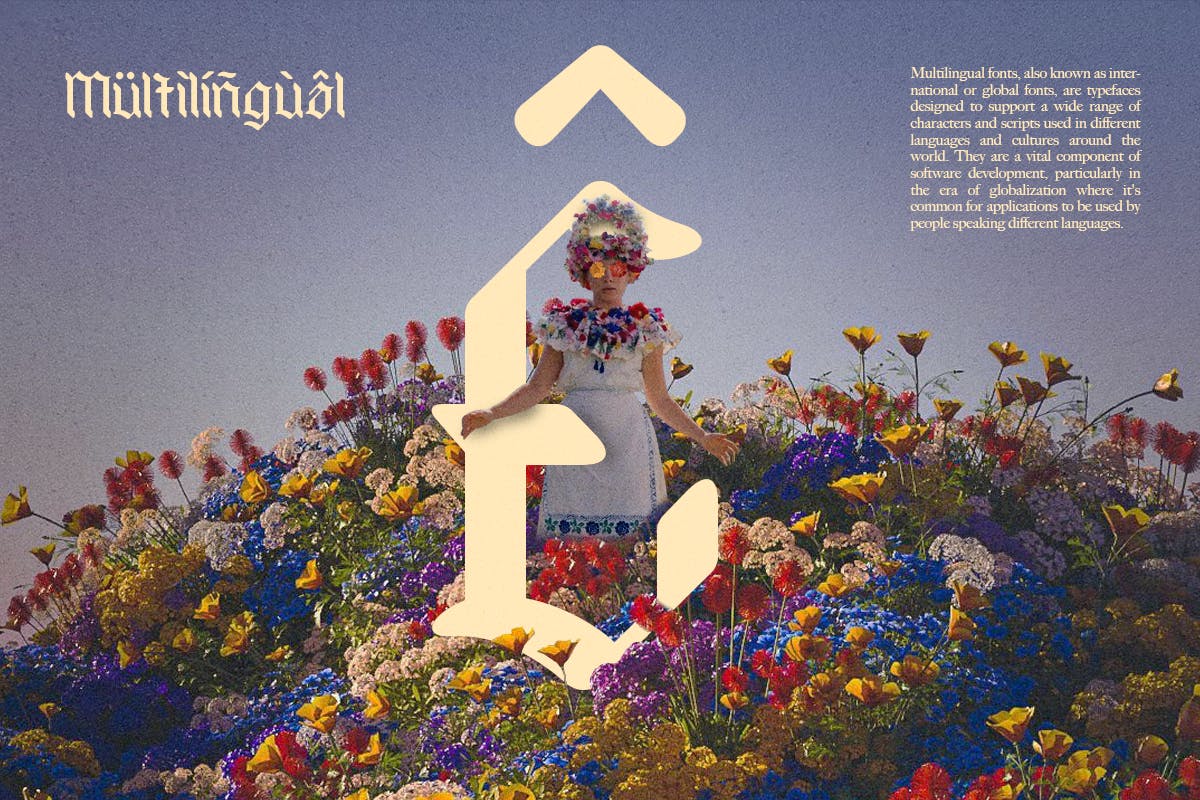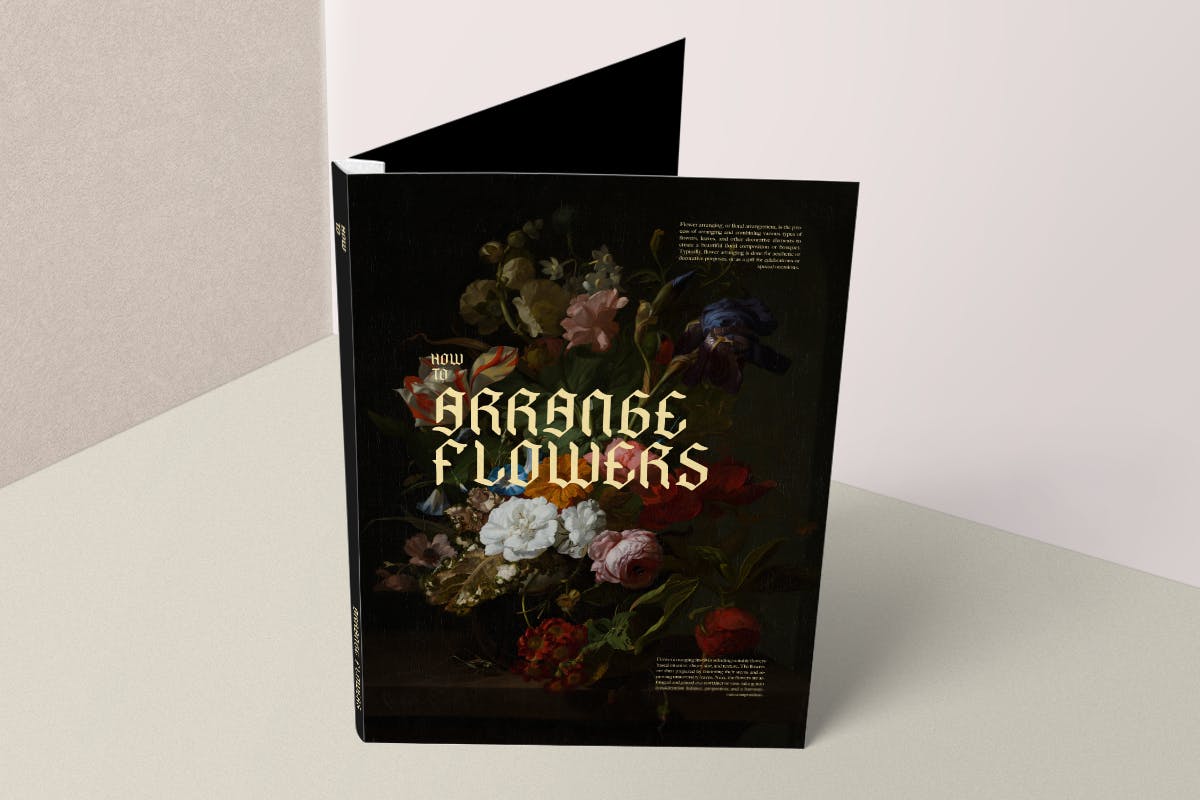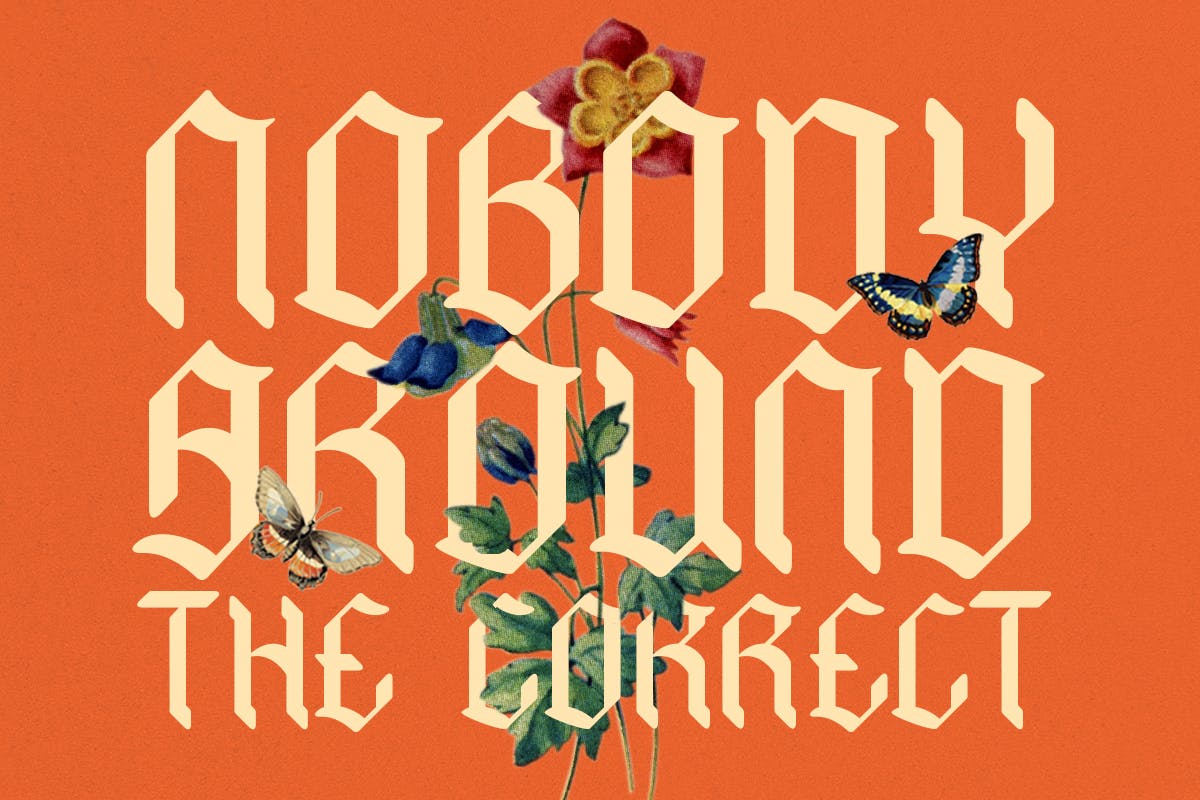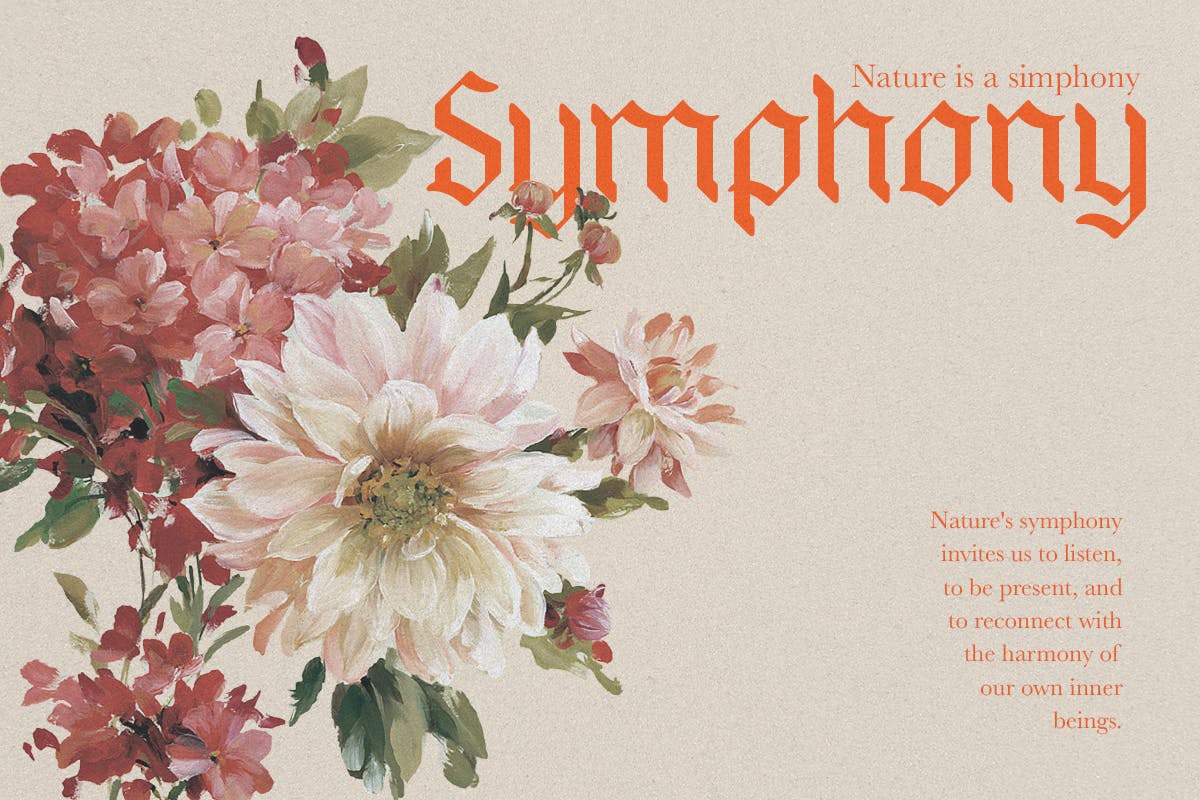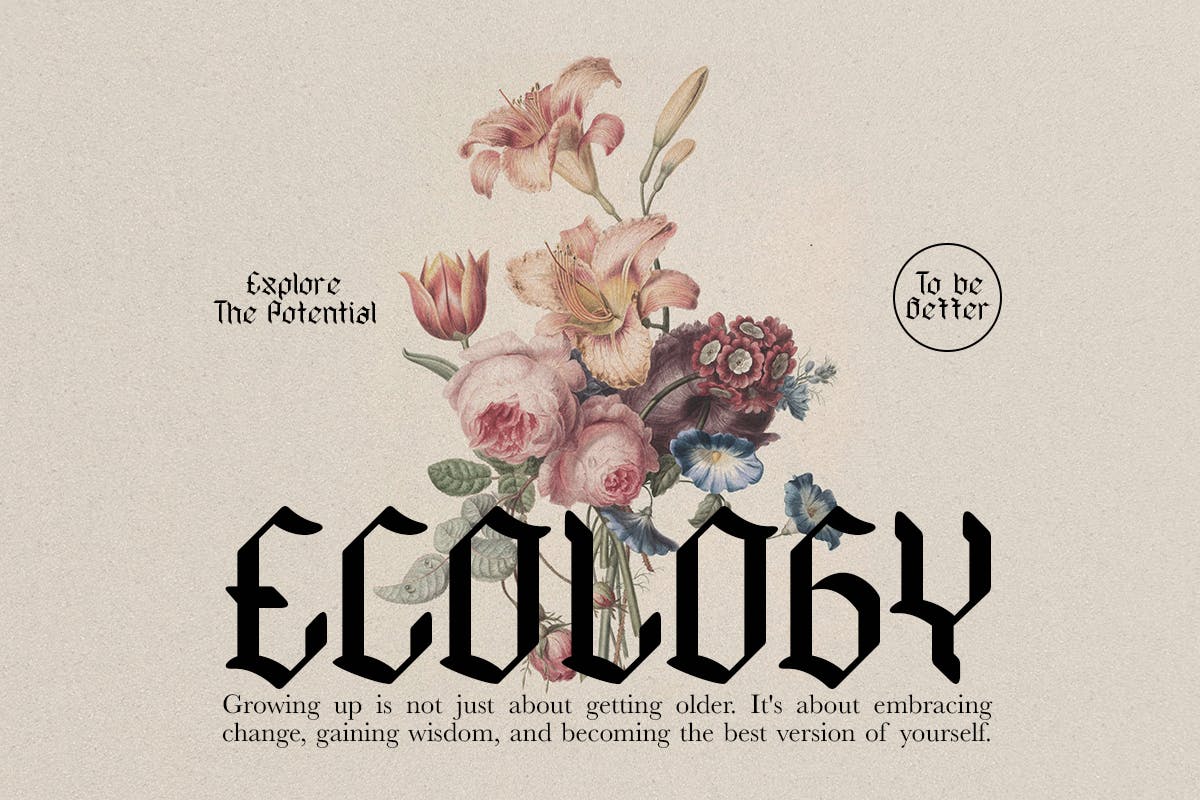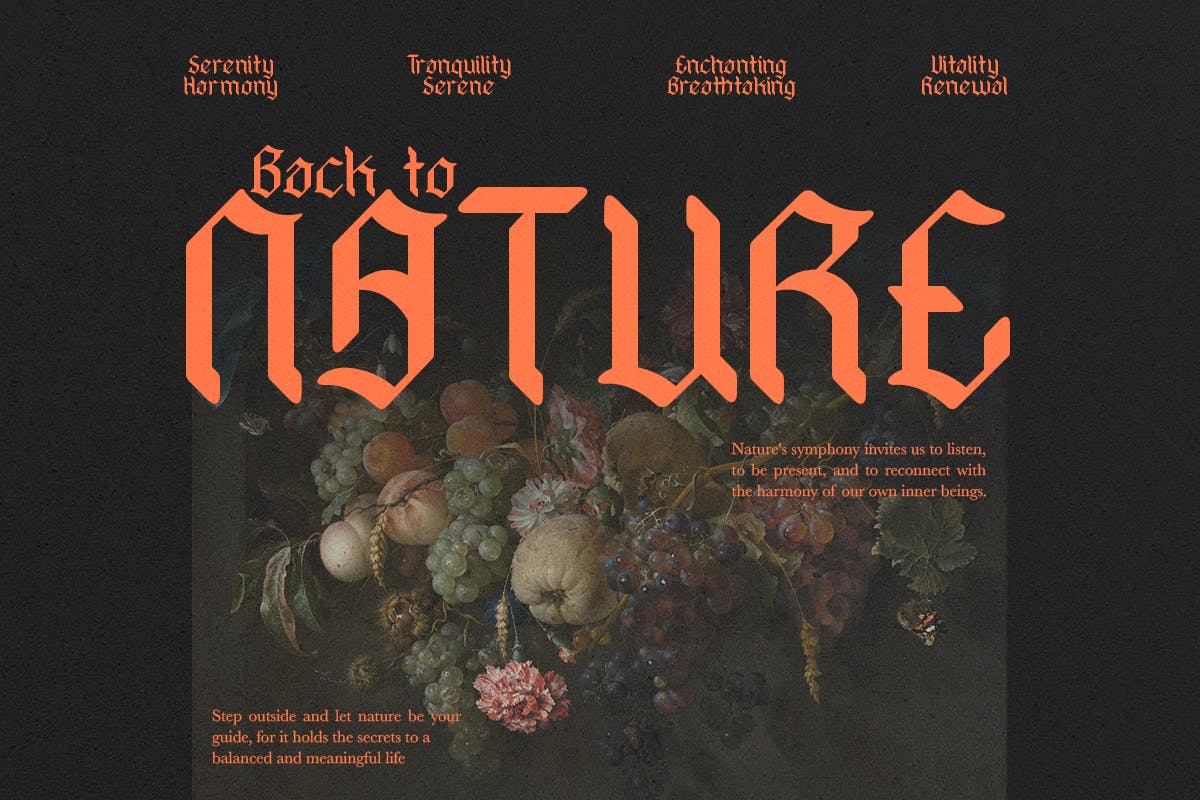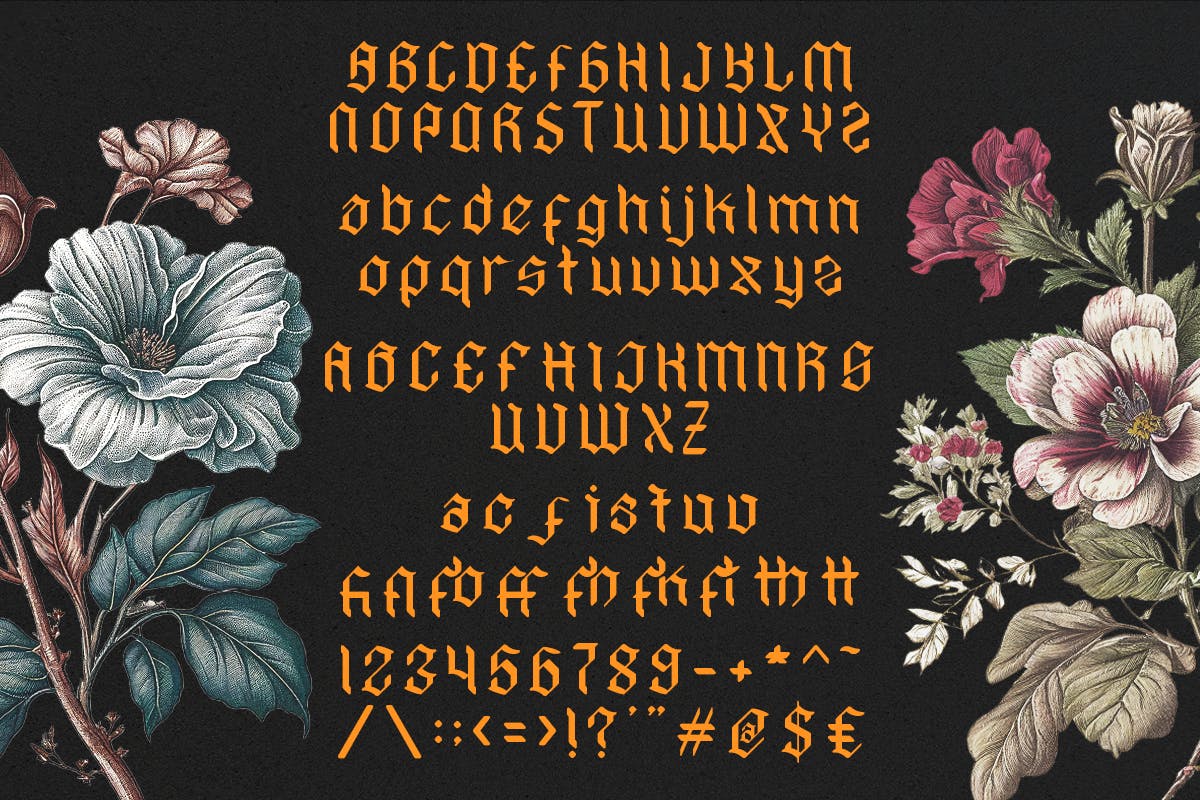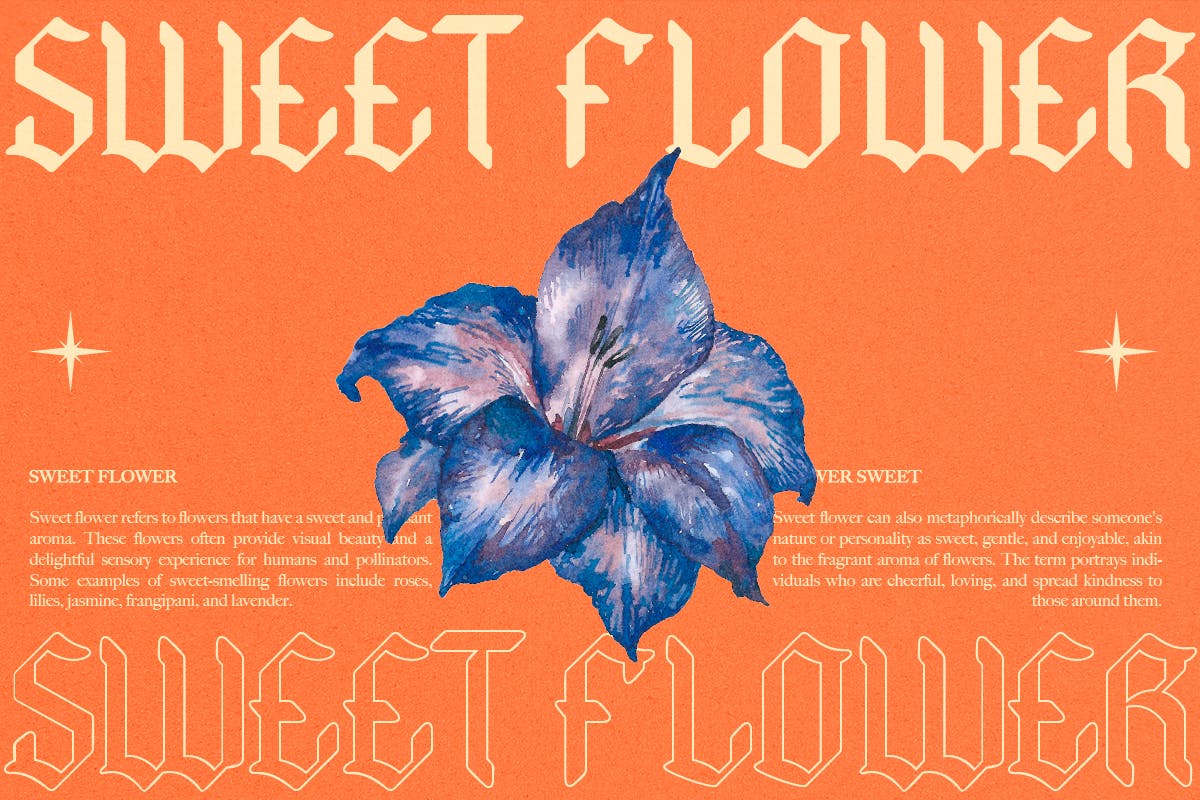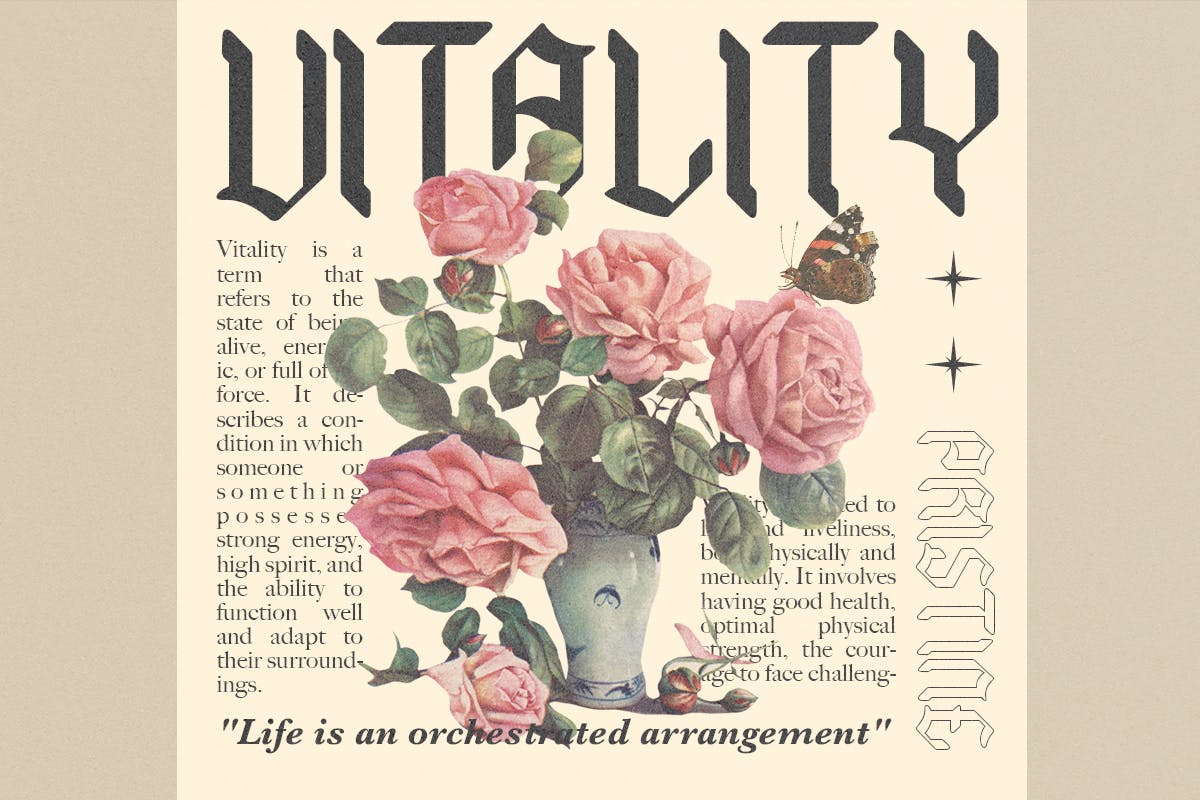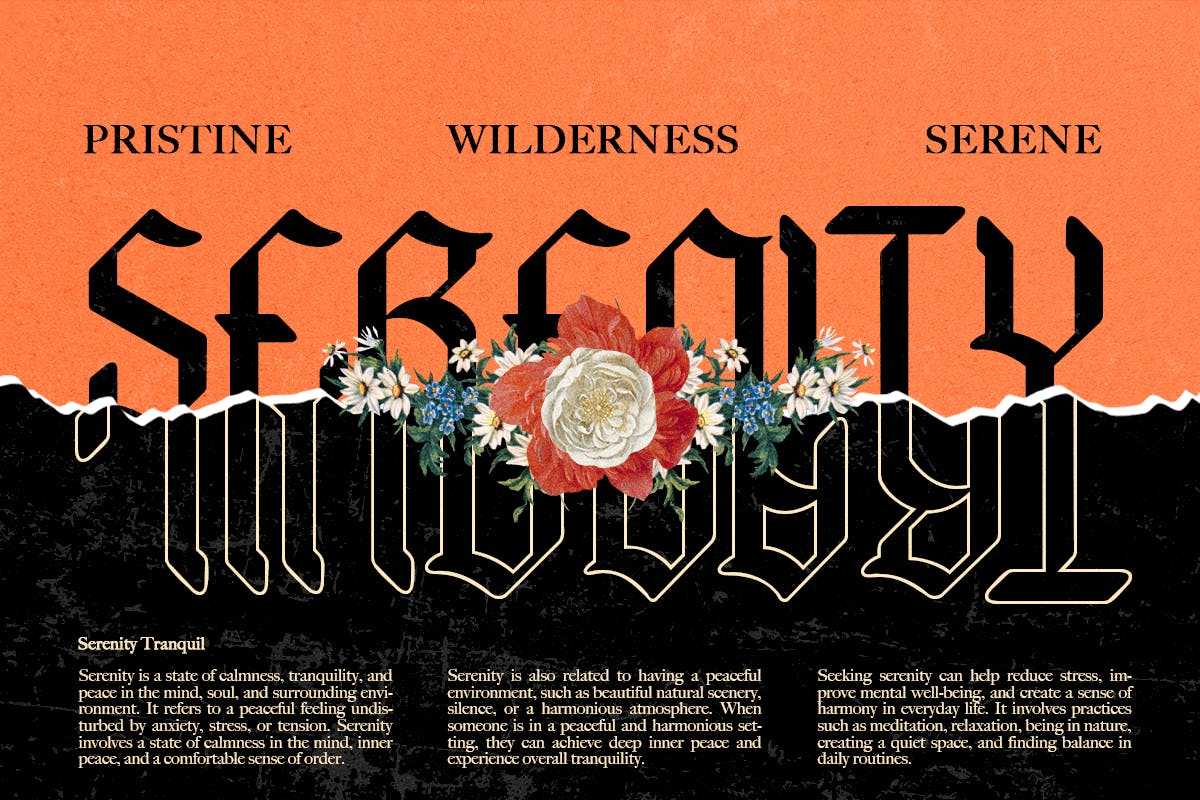
Hyacinth Modern Font
فونت مدرن هایاسیند با طراحی خاص و زیبا، ایده‌آل برای پروژه‌های شما.
به فونت مدرن و شیک هایاسیند (Hyacinth) سلام کنید!
هایاسیند یک فونت مدرن بلک لتر با طراحی گرد است. با سبک مدرن و زیبا، این فونت به پروژه‌های شما جلب توجه می‌کند و الهام‌بخش شما برای خلق آثار منحصر به فرد و مدرن خواهد بود. علاوه بر این، این فونت دارای کاراکترهای جایگزین، لیگاتورها و پشتیبانی از چند زبان است.
فونت هایاسیند برای عناوین، بروشورها، کارت‌های تبریک، بسته‌بندی محصولات، جلد کتاب‌ها، نقل‌قول‌های چاپی، لوگوتایپ، طراحی لباس و جلد آلبوم‌ها ایده‌آل است.
• دارای کاراکترهای جایگزین و لیگاتورهای متعدد
• شکل‌های حروف منحصر به فرد
آماده باشید تا خلاقیت خود را با هایاسیند (HYACINTH) به نمایش بگذارید!